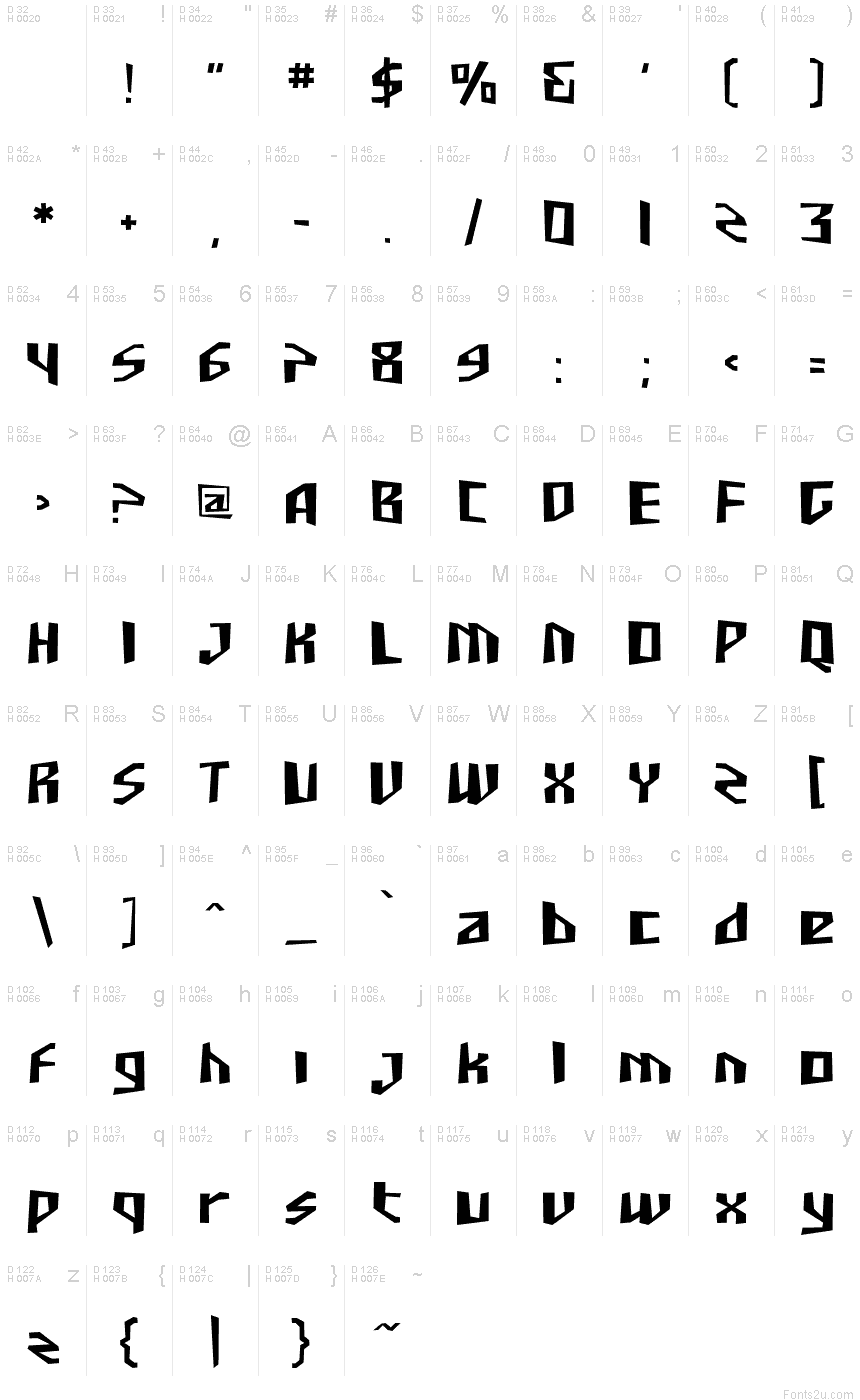
SF Junk Culture od ShyFoundry to darmowy, kanciasty font typu display o technologicznym charakterze i ulicznym, futurystycznym sznycie. Litery wyglądają, jakby zostały wycięte z twardych, czarnych odłamków – mają ostre skosy, nierówne wierzchołki i masywne kształty, które sprawiają wrażenie improwizowanych, a nie precyzyjnie zaprojektowanych. Nadaje to wielkim literom surowy, „poskładany ze śmieci” rytm.
Ta surowa, futurystyczna estetyka świetnie sprawdzi się na nagłówkach plakatów, muzycznych ulotkach, w tytułach gier, na okładkach zinów oraz w brandingu klubów czy kreatywnych eventów, gdzie darmowy font może pozwolić sobie na celową szorstkość. Najlepiej sprawdza się w krótkich formach – szczególnie w logotypach, monogramach i dużych napisach – bo poszarpana geometria i nieoczywisty balans robią tutaj całą robotę.